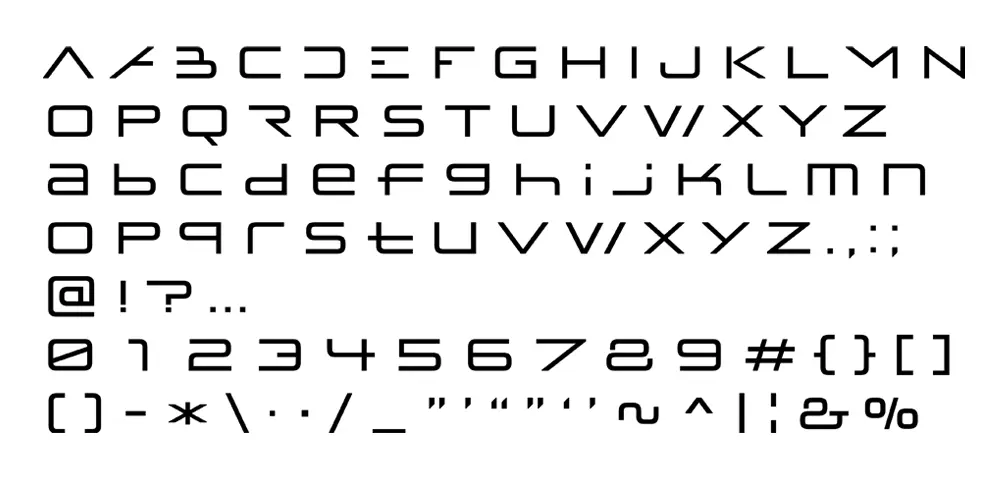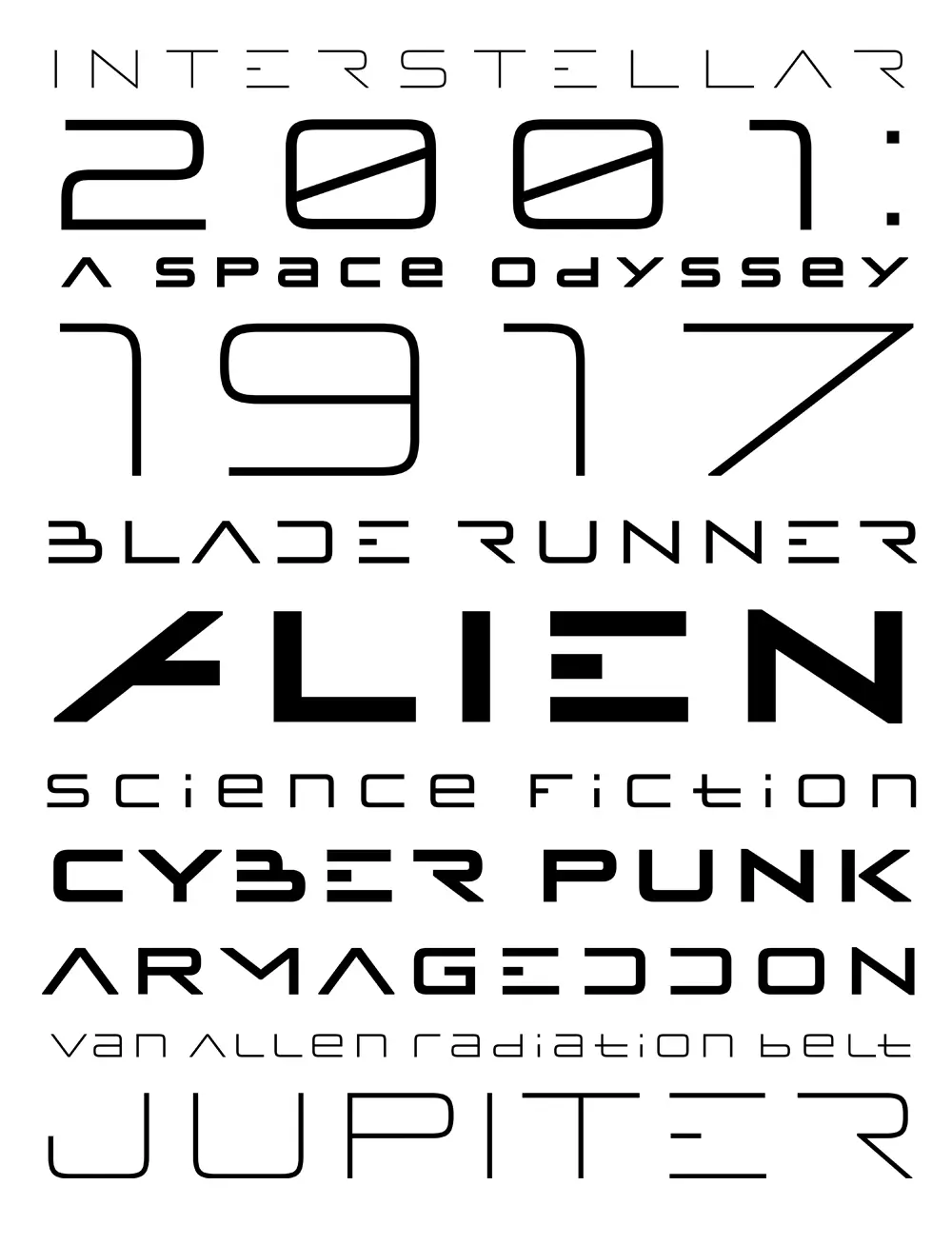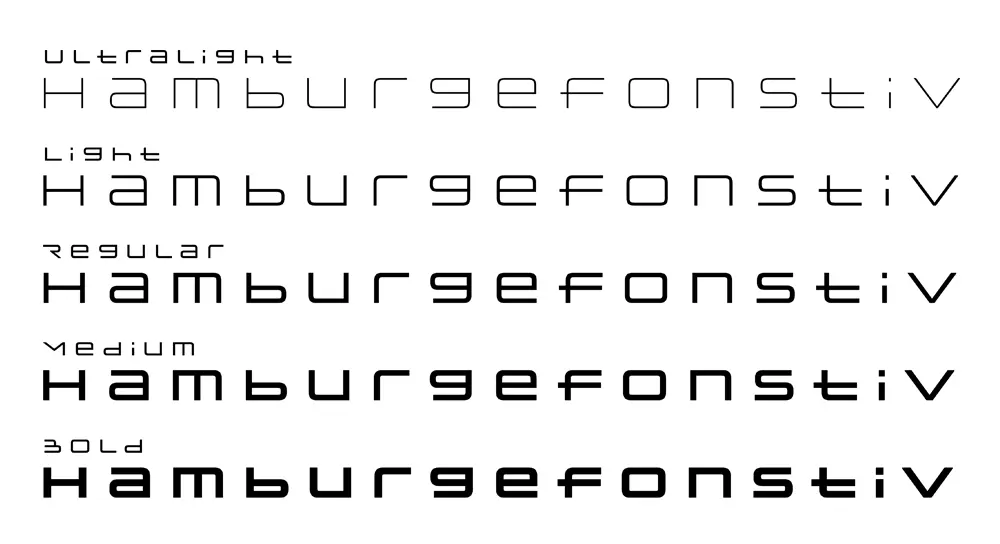
Melete介紹
Melete 是一種無襯線字體,旨在營造科幻電影標題的感覺。
在犧牲一些可讀性的同時,我們創造了慷慨的留白來營造一種未來主義的氛圍。
我們的目標是更加前衛的設計,參考了科幻電影中經常使用的Eurostile Extended和Bank Gothic 。
目前,這是一個測試版本,僅包含基本的大小寫字母、數字和符號。
MeleteはSF映畫のタイトルのような雰囲気を目指したサンセリフです。
可読性を一部犠牲にしつつ、ゆったりとした餘白を用意し近未來的な雰囲気になるよう仕上げました。
よくSF映畫で使われているEurostile ExtendedやBank Gothicを參考に、より尖ったデザインを目指しています。
現在のところ、基本的な大文字・小文字のアルファベット・數字・記號類のみ収録しているベータ版となります。